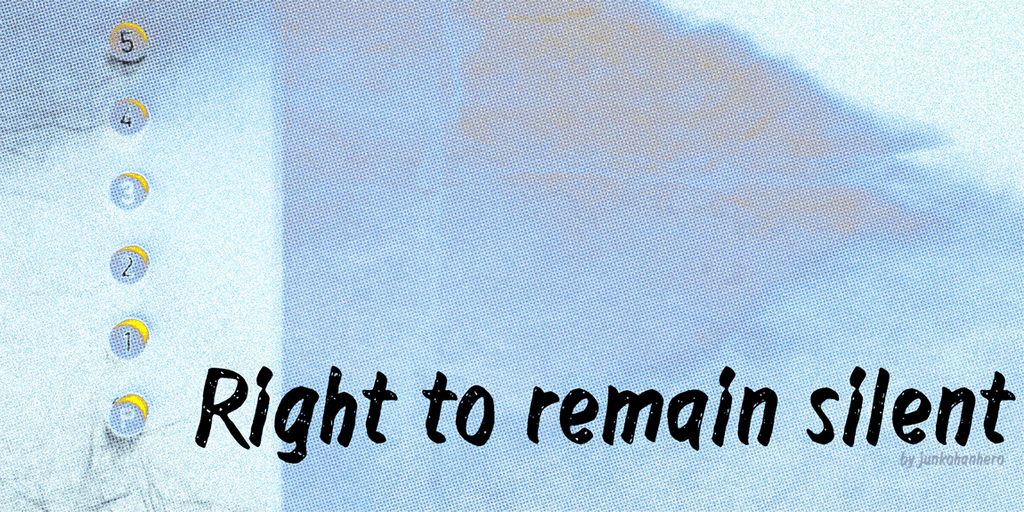
Aqui está uma breve descrição para a página de download da font ‘Right to remain silent’, adaptada ao tom solicitado, sem usar markdown: A Right to remain silent Font é um design leve e moderno criado pelo designer Hamilton. Seja você um entusiasta do design ou alguém simplesmente procurando por novas opções para seu próximo projeto, essa fonte certamente fará as suas delícias. Escolha a personalidade da sua próxima criação com uma fonte que não só ajuda a dar vida à sua ideia, mas também permite-lhe explorar diferentes estilos e tonalidades sem comprometer o estilo original do seu trabalho. Este é um projeto gratuito para uso pessoal de Hamilton, mas para qualquer aplicação comercial, como você desejar adicionar essa fonte ao seu trabalho em destaque, você pode fazer o download comprando a licença comercial por 15 euros ou dólares americanos via PayPal. Se você gostou do design da nossa fonte e quer apoiar o talento de Hamilton, nós sempre estamos buscando mais contribuições. Os donativos regulares são muito bem-vindos para ajudar Hamilton a continuar criando novas maneiras fantásticas de expressar suas ideias através das linguagens visuais. Não importa onde você está no seu projeto, a Right to remain silent Font certamente se encaixa perfeitamente!